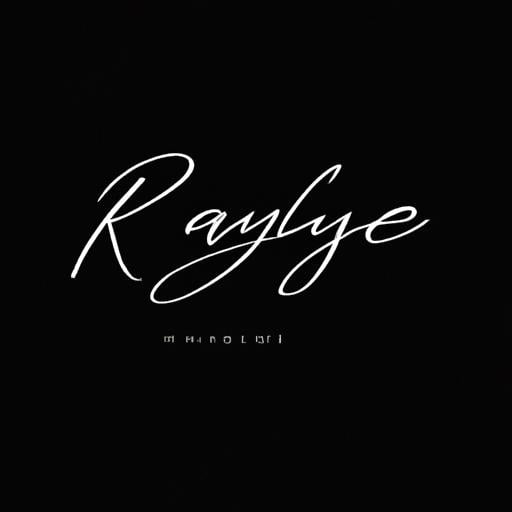
Font chữ ký việt hóa
Font chữ ký việt hóa là những phông chữ đặc biệt được thiết kế riêng để tạo nên các chữ ký cá nhân đẹp mắt, ấn tượng. Khác với những font chữ thông thường, các font chữ ký thường có phong cách độc đáo, mềm mại, uốn lượn và đôi khi kèm theo cả họa tiết trang trí. Điểm đặc biệt của font chữ ký việt hóa là chúng hỗ trợ đầy đủ tiếng Việt, giúp bạn dễ dàng đặt tên hay viết lời chúc mà không lo bị lỗi font. Với sự đa dạng về kiểu dáng, màu sắc, font chữ ký việt hóa chính là công cụ đắc lực để bạn thể hiện cá tính, gu thẩm mỹ trong từng thiết kế.
Top 10 font chữ ký việt hóa đẹp nhất 2024
Font chữ ký SignRathi
Font chữ ký đẹp SignRathi là một phông chữ viết tay mảnh và đẹp mắt, thiết kế tự nhiên với rất nhiều bộ ký tự thay thế. Phông chữ này được thiết kế bởi Dwi Ahidian và Việt hóa bởi Đức Thủy, ra mắt vào năm 2023.
Font chữ ký Manchester
Font chữ ký Manchester là một phông chữ viết tay đẹp và phong cách, được thiết kế bởi Andrey Sharov vào năm 2018. Phông chữ này thường được sử dụng để tạo chữ ký cá nhân, logo thương hiệu, thiệp mời, bài đăng trên mạng xã hội nhờ nét chữ thanh lịch, sang trọng và hiện đại.
Font chữ ký Quick Signature
Font chữ ký Mrattoos Signature
Font Chữ Ký Đẹp Và Sang Trọng Madinah Authentic
Madinah Authentic là font chữ ký đậm chất cổ điển, lấy cảm hứng từ nghệ thuật Ả Rập. Font này có nét chữ viết tay mềm mại, uốn lượn tạo cảm giác sang trọng.
Font Chữ Ký Đẹp Fashion Signature
Fashion Signature là font chữ ký mang phong cách thời trang, hiện đại với những đường nét uốn lượn, thanh mảnh.
Font Chữ Ký Ruthligos Việt Hóa
Font chữ ký Ruthligos Việt hóa mô phỏng nét chữ viết tay tự nhiên, mềm mại với nhiều biến thể nét vẽ khác nhau. Được thiết kế bởi Mats-Peter Forss vào năm 2018, thường được sử dụng trong thiết kế logo, thiệp mời, bao bì sản phẩm.
Font Chữ Kí Quick Signature
Quick Signature là font chữ ký mềm mại, bắt chước nét viết tay tự nhiên của tác giả HPtypework. iểm nổi bật của Quick Signature là các chữ cái thường được Việt hóa với đường nét, vị trí dấu khác biệt, tạo nên phong cách chữ ký cá nhân, độc đáo
Font Chữ Viết Tay Lovepen Việt Hóa Đẹp V2
Lovepen là font chữ viết tay mỏng manh, nhẹ nhàng với nét chữ lả lướt, tạo cảm giác thư pháp tự nhiên. Được thiết kế bởi Lian Types vào năm 2016, thường được sử dụng cho thiết kế poster, nhãn hiệu thời trang và lĩnh vực làm đẹp vì vẻ ngoài thanh thoát, nữ tính.
Font Chữ Ký Đẹp The Billion
The Billion là font chữ ký đẹp với nét chữ viết tay mềm mại, chân thực. The Billion thường được ứng dụng để thiết kế chữ ký, typography, logo, watermark nhờ vẻ ngoài sang trọng, tỉ mỉ.
Font Việt Hóa The Handwritten Watermark
The Handwritten Watermark là một font chữ viết tay đẹp, mềm mại với những đường nét uốn lượn tự nhiên. Font này được thiết kế bởi Joana Pereira vào năm 2015, phù hợp cho các thiết kế poster, lời chào, chữ ký điện tử.